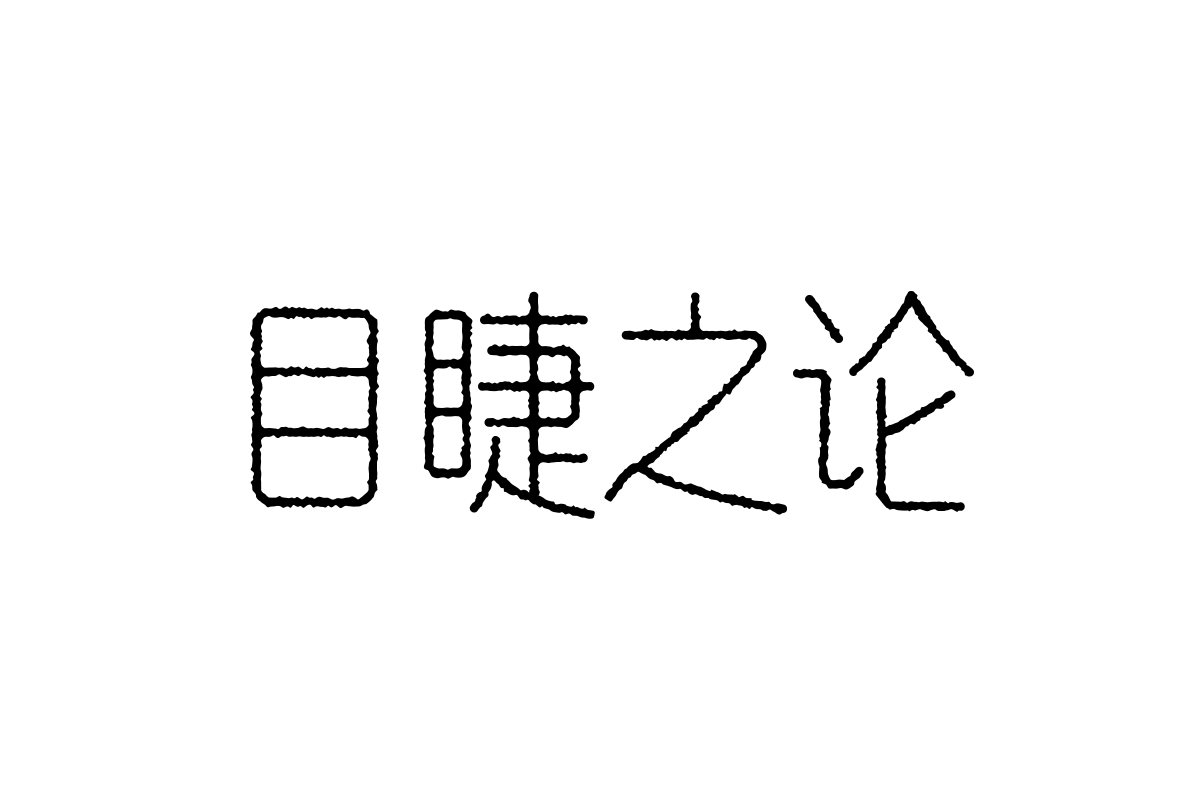
汉仪天诺丽线古韵版是一款由北京汉仪创新推出的字体,其设计灵感来源于古代书法艺术,旨在通过现代技术将古典美感融入现代设计中。这款字体以其独特的风格和广泛的应用前景受到关注。以下是对该字体的具体介绍:
1. **字体家族与风格**:汉仪天诺丽线古韵版隶属于汉仪创新的字体家族,提供了多种风格的字体样式,包括简体和繁体版本。这种多样化的风格使得设计师可以根据不同的项目需求选择合适的字体样式。
2. **字符数量与分布**:该字体包含7628个字符,覆盖了广泛的字符集,这为文字设计和排版提供了极大的灵活性。无论是需要大量文字还是精细的文本排版,汉仪天诺丽线古韵版都能提供足够的字符资源。
3. **字体特点与应用**:汉仪天诺丽线古韵版的设计风格独特,具有浓厚的古典韵味,适合用于需要展现传统文化特色的设计项目。例如,在书籍、杂志、广告以及网页设计中,这款字体能够很好地传达出古典美的感觉,增加视觉上的吸引力。
总的来说,汉仪天诺丽线古韵版不仅是一款美观的字体,它的设计还体现了对传统文化的尊重和传承。这款字体因其独特的风格和广泛的应用潜力,成为了设计师们不可或缺的工具之一。